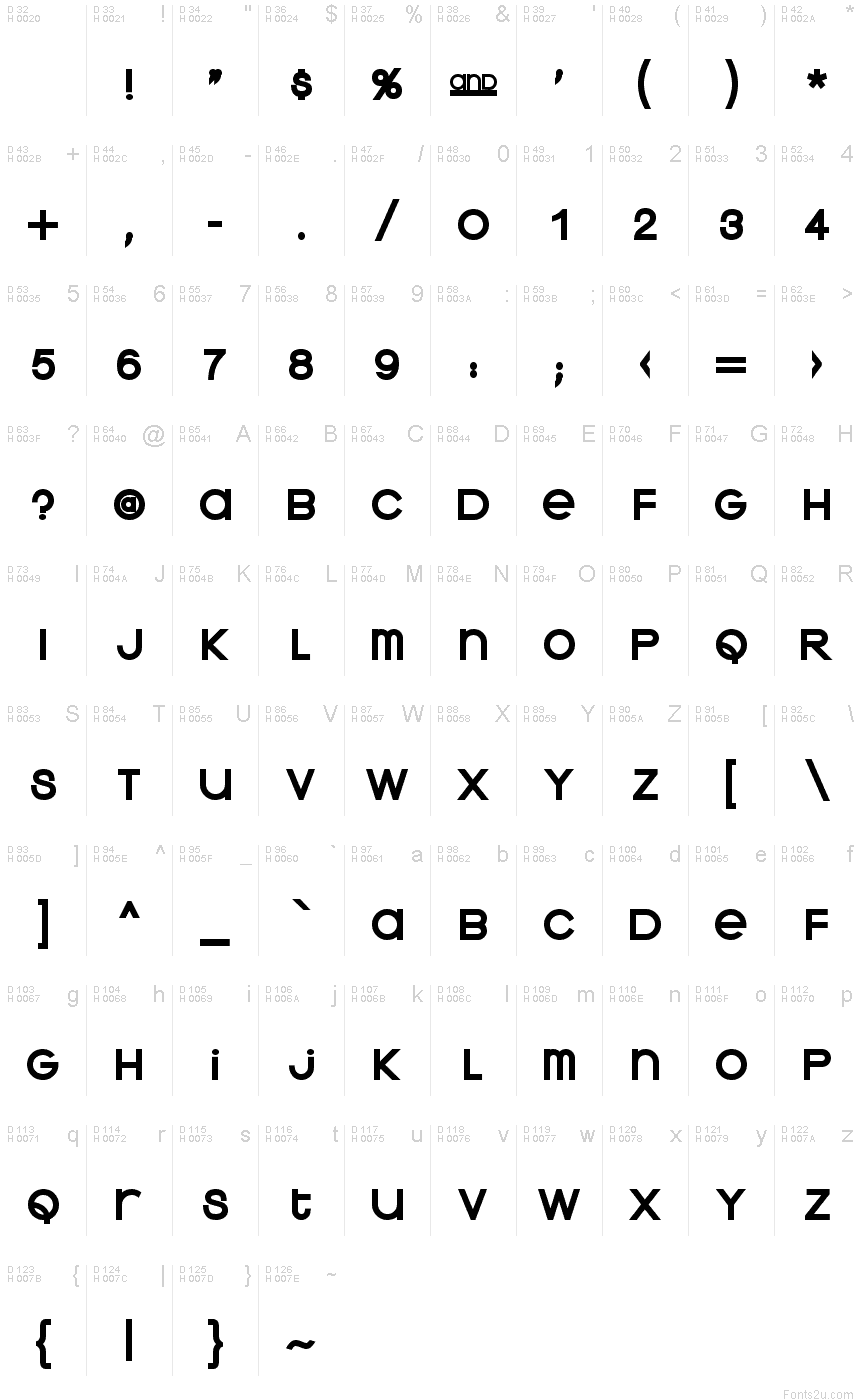
Kravitz Extra Thermal od Fontalicious to darmowy krój typu display o zaokrąglonych, geometrycznych kształtach i ostrych przekątnych cięciach. Litery łączą w sobie płynne krzywizny z prostymi liniami, co nadaje krojowi kompaktowy, surowy rytm, który sprawia wrażenie bardziej konstrukcyjnego niż dekoracyjnego.
Kravitz Extra Thermal świetnie sprawdza się w logotypach, nagłówkach plakatów, okładkach albumów, opakowaniach i grafikach eventowych, ponieważ jego wyraźne kształty zachowują czytelność przy dużym rozmiarze i krótkich tekstach. Ten darmowy font pasuje również do cytatów redakcyjnych i banerów internetowych, gdy szukasz graficznego stylu nagłówków, który opiera się na formie, a nie na zdobnictwie.